26 melhores fontes de ficção científica de 2023 (gratuitas e premium)
Publicados: 2023-09-16Você é um designer gráfico em busca da fonte de ficção científica perfeita para aprimorar o design do seu projeto? Bem, não procure mais! Nesta postagem do blog, apresentamos as 26 melhores fontes de ficção científica que certamente levarão seus designs a um nível totalmente novo.
Mas primeiro, você deve estar se perguntando: por que devo me preocupar com fontes de ficção científica? Eles realmente valem o hype?
Bem, deixe-me esclarecê-lo. As fontes de ficção científica ganharam muitos seguidores ao longo dos anos, graças ao seu apelo futurista e sobrenatural. Essas fontes são perfeitas para projetos que exigem um toque de inovação, seja um pôster de filme, um videogame ou a capa de um livro de ficção científica.
Com suas linhas elegantes, ângulos agudos e formatos de letras exclusivos, as fontes de ficção científica têm o poder de chamar a atenção instantaneamente e transportar seu público para uma dimensão totalmente nova. Agora, isso não é algo que você deseja para seus projetos?
Então, sem mais delongas, vamos mergulhar direto em nossa coleção das 26 melhores fontes de ficção científica. Cada fonte foi cuidadosamente selecionada com base em sua estética, versatilidade e impacto geral. Exploraremos uma variedade de estilos, desde futuristas e minimalistas até designs mais elaborados e ornamentados.
Esteja você procurando uma fonte que grite cyberpunk, incorpore aventuras intergalácticas ou simplesmente adicione um toque de charme extraterrestre, nós temos o que você precisa.
Então sente-se, relaxe e prepare-se para descobrir a fonte de ficção científica perfeita para o seu próximo projeto.
Melhores fontes premium de ficção científica
Quer levar seus projetos de design gráfico para uma nova dimensão? Basta procurar nossa seleção escolhida a dedo das melhores fontes premium de ficção científica.
Essas fontes impressionantes adicionarão um toque de outro mundo aos seus designs, dando-lhes um toque verdadeiramente fora deste mundo. Então vá em frente, mergulhe em nossa coleção selecionada e explore as possibilidades!
Graxa
Grease é uma fonte moderna de ficção científica que adiciona um toque de elegância e fluidez aos seus designs. Com seu delicado estilo manuscrito, traz uma mistura única de ligaduras e elementos ondulados.
Sua beleza e versatilidade fazem dele a escolha perfeita para designers que buscam valorizar seus projetos com um toque de sofisticação.
Esta fonte se destaca por suas curvas graciosas e formatos de letras cativantes. As ligaduras e os elementos ondulados adicionam uma camada extra de criatividade e interesse visual, permitindo criar composições impressionantes.
É perfeito para designs digitais e impressos, quer você esteja trabalhando em branding, tipografia ou qualquer outro projeto criativo.
Grease traz uma sensação de beleza e exclusividade aos seus designs. Sua elegância artesanal adiciona um toque pessoal e chama a atenção sem esforço. As linhas fluidas e os detalhes intrincados criam uma experiência visual cativante que diferenciará seus designs da multidão.
Cabos
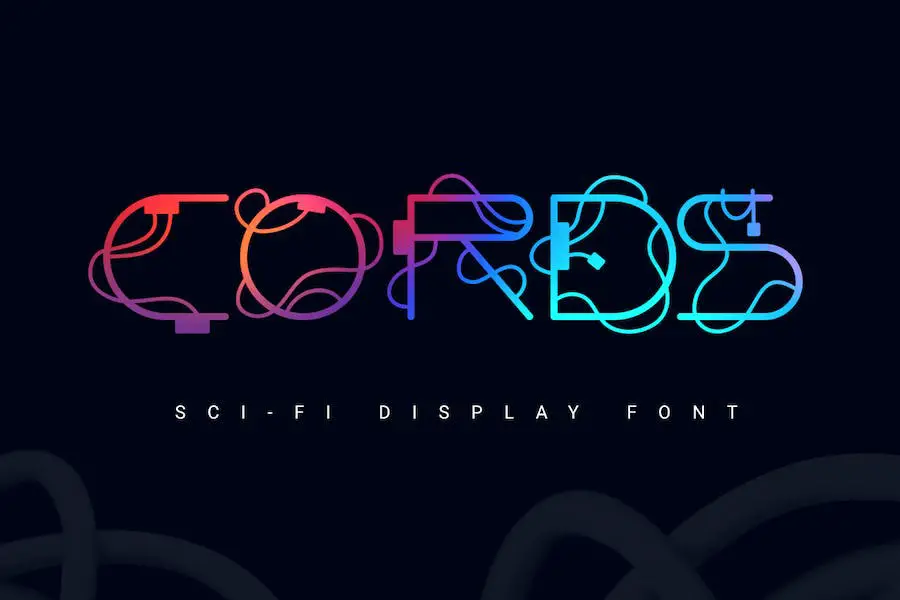
Cords é uma fonte sem serifa exclusiva e elegante que apresenta letras e fios arredondados, dando-lhe uma vibração futurística e de ficção científica. Inspirada no icônico filme Matrix, esta fonte adiciona um toque de emoção e modernidade a qualquer design.
Com letras maiúsculas e capacidade de funcionar bem com fundos claros e escuros, Cords é perfeito para criar títulos curtos atraentes e visualmente atraentes.
A adição de cores às letras realça ainda mais o design geral, tornando-o perfeito para designers gráficos que desejam levar seus projetos para o próximo nível.
Andoria
Andoria é uma fonte moderna projetada para declarações de moda, ficção científica, cinematográficas e exclusivas. Ele tem um charme especial que o torna perfeito para belos títulos, marcas, logotipos e uso em display. Seu design elegante e moderno adiciona um toque de sofisticação a qualquer projeto.
Quer você seja um designer gráfico em busca de aprimorar seus projetos ou um entusiasta da moda que queira fazer uma declaração ousada, Andoria é a escolha perfeita. A versatilidade da fonte permite que ela seja utilizada em diversos contextos, tornando-a obrigatória para designers que buscam elevar seu trabalho.
Esteja você trabalhando em uma capa de revista, um pôster de filme ou um logotipo de roupa, as linhas simples e curvas elegantes de Andoria irão capturar a atenção e deixar uma impressão duradoura.
Com Andoria, seus designs se destacarão da multidão e causarão um impacto memorável. Então, por que esperar? Dê aos seus projetos um toque moderno e elegante com Andoria.
JEDAR
JEDAR é uma fonte techno-sci-fi projetada para quem precisa de uma tipografia de destaque, especialmente para displays, pôsteres e projetos tecnológicos ou astronômicos. Com seus caracteres nítidos e semelhantes a símbolos, esta fonte adicionará um toque de estilo futurista aos seus designs.
Esta fonte de ficção científica é perfeita para dar aos seus projetos um toque futurista e de alta tecnologia. Seus símbolos exclusivos e formatos de caracteres nítidos fazem com que ele se destaque e chame a atenção.
Esteja você projetando um pôster, criando exibições atraentes ou trabalhando em um projeto tecnológico ou astronômico, JEDAR é a fonte que levará seu design para o próximo nível.
As formas nítidas e elegantes dos caracteres do JEDAR lembram símbolos, dando ao seu texto uma aparência distinta e futurística. É perfeito para capturar a essência da tecnologia e as maravilhas do cosmos.
Se você deseja transmitir uma sensação de inovação, explorar o desconhecido ou simplesmente adicionar um toque de ficção científica aos seus designs, esta fonte tem o que você precisa.
Lespace
Lespace é uma fonte de ficção científica moderna do estúdio Drizy, perfeita para seus projetos de ficção científica techno. Com sua variedade de estilos básicos, esta fonte foi projetada especificamente para aprimorar qualquer projeto temático de ficção científica. Criada pelo estúdio Drizy, Lespace oferece tudo que você precisa em uma fonte de ficção científica.
Lespace by Drizy studio é uma fonte moderna e elegante, perfeita para adicionar um toque futurista aos seus projetos. Esteja você projetando um site, criando um logotipo ou trabalhando em uma obra de arte com tema de ficção científica, Lespace tem todos os estilos básicos de que você precisa para dar vida à sua visão.
Esta fonte techno-sci-fi foi projetada com linhas elegantes e bordas nítidas, dando-lhe uma aparência futurista e de alta tecnologia. O design exclusivo da Lespace a diferencia de outras fontes e a torna uma escolha de destaque para qualquer projeto que necessite de uma estética moderna e vanguardista.
Explorar Rover
Rover Explore é uma fonte de ponta que incorpora o futuro e a tecnologia. Ele se enquadra na categoria Futurista e oferece uma mistura perfeita de elementos de techno, ficção científica e estilo espacial.
Se você é um designer gráfico que busca elevar seus projetos com um toque futurista, esta fonte é obrigatória.
Com o Rover Explore, você obtém acesso a uma coleção de 26 fontes de ficção científica de primeira linha. Cada fonte carrega seu próprio estilo único, permitindo que você experimente e encontre a combinação perfeita para seu projeto específico.
Esteja você projetando um site, logotipo, pôster ou qualquer outro empreendimento criativo, essas fontes adicionarão um toque de sofisticação e inovação.
Essas fontes techno-sci-fi são projetadas com precisão e atenção aos detalhes, garantindo que se integrem perfeitamente aos seus designs. A estética elegante e futurista do Rover Explore irá captar a atenção e deixar uma impressão duradoura.
É a escolha perfeita se você deseja criar uma sensação de tecnologia avançada e de outro mundo em seus projetos.
Rochas Espaciais!
Rochas Espaciais! é uma fonte retrô de ficção científica inspirada nas icônicas séries de televisão da década de 1950. Com seu charme vintage e vibrações futuristas, esta fonte é perfeita para designers gráficos que buscam adicionar um toque de nostalgia e estilo da era espacial aos seus projetos.
Os atributos únicos do Space Rocks! faça com que ela se destaque entre outras fontes da categoria. Suas letras ousadas e angulares capturam a essência da ficção científica retrô, transportando instantaneamente os espectadores para uma época de discos voadores e aventuras intergalácticas.
Essa fonte é altamente versátil e pode ser usada para diversos fins de design, desde a criação de logotipo até pôsteres e muito mais.
As linhas limpas e os personagens bem definidos de Space Rocks! garantem legibilidade mesmo em tamanhos maiores, tornando-o ideal para títulos e textos impactantes.
Sua natureza lúdica e atraente o torna uma ótima opção para títulos e cabeçalhos, chamando instantaneamente a atenção e adicionando um toque de personalidade a qualquer design.
Galáxia
Galax é uma nova fonte de ficção científica chamada 'GRVS It' que é perfeita para adicionar um toque futurista ao logotipo de sua equipe ou comunidade. Com seu design elegante e moderno, é a escolha ideal para designers gráficos que buscam aprimorar seus projetos com um tema de ficção científica.
Esta fonte foi criada especificamente para trazer uma sensação de futurismo e criatividade aos seus designs. É perfeito para filmes de ficção científica, videogames ou qualquer projeto que precise de um toque futurista e moderno. É versátil e pode ser usado de várias maneiras para destacar seus designs.
A fonte Galax apresenta letras exclusivas e complexas que certamente chamarão a atenção do seu público. Seu design arrojado e contemporâneo facilita a leitura e acrescenta um toque de profissionalismo a qualquer projeto.
Quer você esteja desenhando um logotipo ou criando um pôster, Galax dará ao seu trabalho uma aparência distinta e moderna.
Uma das grandes vantagens do Galax é a sua adaptabilidade. Ele pode ser redimensionado, dimensionado e manipulado para caber em qualquer projeto sem perder qualidade ou legibilidade.
Isso o torna perfeito para designs impressos e digitais. Ele também suporta diferentes idiomas, para que você possa criar projetos em diferentes idiomas sem complicações.
Bronze de ficção científica
Apresentando Sci Fi Bronze, uma fonte de ficção científica fantástica que pode levar seus projetos de design a um nível totalmente novo. Com seu visual moderno e futurista, esta fonte é perfeita para designers gráficos que desejam adicionar um toque de ficção científica às suas criações.
Uma das características de destaque do Sci-Fi Bronze é seu design elegante e moderno. As linhas limpas e bordas nítidas conferem-lhe um toque futurista, tornando-o a escolha perfeita para qualquer projeto que necessite de um visual moderno e contemporâneo.
Outro grande atributo desta fonte é a sua versatilidade. Esteja você trabalhando em um pôster, logotipo ou design de site, o Sci-Fi Bronze pode se adaptar a qualquer estilo e tema. É uma fonte que pode realmente melhorar a estética geral do seu projeto e destacá-lo da multidão.
Além de sua aparência marcante, Sci-Fi Bronze também oferece uma ampla gama de caracteres e glifos.
Com um extenso conjunto de caracteres, incluindo letras maiúsculas e minúsculas, números e símbolos especiais, você terá todas as ferramentas necessárias para criar designs cativantes e visualmente atraentes.
Surto Sônico
Sonic Surge é uma fonte de exibição ousada e autêntica que celebra formas abstratas em todo o seu brilho eclético. Com seu design elegante e futurista, esta fonte é perfeita para designers gráficos que buscam adicionar um toque de ficção científica aos seus projetos.
As letras fortes e ousadas da fonte marcam presença, capturando a atenção e adicionando uma sensação de energia a qualquer design. Suas formas abstratas e estilo único de letras conferem-lhe uma aparência distinta e moderna que certamente impressionará.
Esteja você trabalhando em um pôster, logotipo ou design de site, o Sonic Surge aprimorará o apelo visual do seu projeto e o destacará da multidão. Sua versatilidade permite que funcione bem tanto em títulos grandes quanto em textos menores, proporcionando flexibilidade em suas escolhas de design.
Uma das características de destaque do Sonic Surge é a atenção aos detalhes. Cada carta é cuidadosamente elaborada, garantindo consistência e legibilidade. As linhas limpas e bordas nítidas da fonte criam uma sensação de precisão, aumentando sua estética futurista.
Andro Futurista
Andro Futuristic é uma fonte hipnotizante sem serifa que exala uma vibração futurística. Esta fonte foi meticulosamente elaborada com atenção precisa aos detalhes, resultando em curvas perfeitas e um design impecável.
Com a sua versatilidade, o Andro Futuristic pode complementar perfeitamente uma vasta gama de projetos, permitindo-lhe libertar a sua criatividade sem restrições.
Esteja você projetando um pôster de filme de ficção científica, um site futurista ou um logotipo inovador, Andro Futuristic é a fonte ideal. Sua aparência elegante e polida irá cativar o seu público, mergulhando-o instantaneamente em um mundo futurista.
A fonte Andro Futuristic possui uma ampla gama de atributos que a tornam obrigatória para designers gráficos. Oferece uma estética clean e minimalista, perfeita para conseguir um visual moderno e vanguardista.
As curvas contínuas e as linhas suaves da fonte garantem legibilidade e harmonia visual, melhorando o apelo geral de seus designs.
Arcádia
Arcadia – uma fonte de exibição Sans Serif para jogos esportivos elegante e moderna que é perfeita para todos os seus próximos projetos de design. Quer você seja um designer gráfico em busca de aprimorar seus projetos ou simplesmente alguém que aprecia uma boa tipografia, a Arcadia está aqui para fazer uma declaração.
Com sua vibração esportiva e futurista, Arcadia adiciona um toque de emoção e energia a qualquer design. As linhas simples e as formas arrojadas desta fonte a tornam ideal para títulos, logotipos e materiais de branding.
Ele realmente captura a essência do gênero de ficção científica, tornando-o obrigatório para designers que trabalham em projetos futuristas ou relacionados à tecnologia.
Arcadia possui uma gama de atributos atraentes que a diferenciam de outras fontes. Em primeiro lugar, o seu design sem serifa confere-lhe um aspecto contemporâneo e minimalista, tornando-o incrivelmente versátil.
Esteja você trabalhando em um pôster, site ou até mesmo em uma interface de jogo, o Arcadia garantirá que seu texto se destaque e chame a atenção.
MORTON
MORTON é uma fonte que captura a essência do vasto e curioso mundo do espaço. Com seu design exclusivo, permite explorar este reino fascinante em seus projetos de design gráfico.
As letras maiúsculas apresentam um recorte no canto, adicionando um toque diferenciado, enquanto as letras minúsculas permanecem totalmente fixadas para um visual coeso.
O design da MORTON é perfeito para adicionar um clima de ficção científica aos seus projetos. Seus cantos recortados dão uma sensação ousada e futurista, enquanto as letras minúsculas totalmente anexadas mantêm uma sensação de coesão. Esta fonte é ideal para transmitir a maravilha e o mistério do espaço em seus designs.
Uma das características de destaque da MORTON é a sua versatilidade. Esteja você trabalhando em um pôster, site ou logotipo, essa fonte pode se adaptar perfeitamente a vários projetos de design. Suas linhas simples e estilo exclusivo o tornam uma excelente escolha para qualquer design de ficção científica ou com tema espacial.
Galáxia
Galaxy é uma fonte modular, geométrica e levemente condensada que visa aprimorar a exibição de seus projetos. Como designer gráfico em busca de fontes para elevar seus designs, o Galaxy apresenta uma excelente opção.
Com características únicas, essa fonte se destaca e acrescenta um toque de sofisticação ao seu trabalho.
O design modular do Galaxy permite fácil organização e personalização, tornando-o versátil para uma ampla gama de projetos. Sua natureza geométrica confere uma aparência clean e moderna, enquanto o estilo condensado ajuda a garantir que seu texto permaneça compacto e visualmente atraente.
Esteja você trabalhando em pôsteres, logotipos ou materiais de marca, o Galaxy pode trazer uma sensação de elegância e profissionalismo. Seu design focado na exibição o torna perfeito para chamar a atenção do espectador e criar um impacto visual memorável.
Atecha Sport
'Atecha Sport é uma fonte que se inspira nos mundos emocionantes dos jogos, tecnologia e esportes. Captura a essência do progresso e da inovação nestas áreas, tornando-o uma escolha perfeita para designers gráficos que procuram aprimorar os seus projetos com um toque de estilo futurista.
Com o seu design elegante e moderno, o Atecha Sport exala uma sensação de energia e dinamismo. Ele adiciona um elemento único e atraente a qualquer design, seja um logotipo de jogo, um pôster esportivo ou um site com tema tecnológico.
A estética ousada e futurista das fontes faz com que elas se destaquem da multidão, deixando uma impressão duradoura nos espectadores.
A versatilidade do Atecha Sport é outro aspecto que o diferencia. Adapta-se perfeitamente a vários contextos de design, seja digital ou impresso. Suas linhas limpas e nítidas tornam-no facilmente legível em diferentes tamanhos, garantindo que sua mensagem chegue claramente ao seu público.
Esteja você trabalhando em um site, no layout de uma revista ou em um gráfico de mídia social, Atecha Sport é uma escolha confiável que oferece resultados.
Leegione
Leegione é uma fonte futurista de ficção científica neon que adiciona um toque único e cativante aos seus projetos. Com seu estilo futurista, esta fonte é perfeita para criar logotipos atraentes que deixarão uma impressão duradoura.
Esteja você projetando um pôster de filme de ficção científica ou um site de alta tecnologia, Leegione certamente levará seu projeto para o próximo nível.
O design elegante e moderno da Leegione faz com que ela se destaque de outras fontes. Seu brilho neon e bordas nítidas dão uma sensação futurística, transportando instantaneamente os espectadores para um mundo de ficção científica.
Essa fonte é versátil e funciona bem em aplicações ousadas e sutis, tornando-a uma ótima opção para uma ampla variedade de projetos.
Uma das grandes vantagens de Leegione é a sua legibilidade. Apesar de seu design futurista, a fonte permanece legível e não sacrifica a clareza pelo estilo. Isto garante que a sua mensagem será sempre transmitida com clareza, mesmo nos designs mais visualmente marcantes.
Quadros Espaciais
Space Boards é uma fonte sans-based que oferece uma combinação única de caracteres minúsculos e maiúsculos, dando aos seus designs uma aparência futurista e moderna.
Esta fonte é perfeita para designers gráficos que buscam aprimorar o design geral de seus projetos, incorporando um toque de estética de ficção científica.
Com sua aparência elegante e moderna, Space Boards certamente chamará a atenção dos espectadores e adicionará um toque contemporâneo a qualquer design.
Esteja você trabalhando em um logotipo, pôster ou site, esta fonte é uma ótima opção para criar um design visualmente impressionante e inovador.
Satélite
Sattelar é uma fonte futurística inspirada em ficção científica, filmes e livros. Ele adiciona um toque futurista aos seus projetos de design, capturando a essência do gênero de ficção científica.
Com seu design elegante e moderno, Sattelar é perfeito para criar manchetes, títulos e logotipos atraentes que transportam instantaneamente seu público para um mundo futurista.
Os atributos da Sattelar são o que a diferenciam das demais fontes. Suas linhas simples e formas geométricas conferem-lhe um visual elegante e moderno, tornando-o ideal para designs contemporâneos.
Esteja você trabalhando em um pôster para uma convenção de ficção científica ou projetando um site para uma empresa de tecnologia, o estilo futurista da Sattelar dará aos seus projetos uma sensação única e inovadora. Sua versatilidade permite que seja utilizado em diversas aplicações de design, seja em mídia impressa ou digital.
Melhores fontes de ficção científica gratuitas
Quer levar seus projetos de design gráfico para o próximo nível? Não procure mais, nossa seleção das melhores fontes de ficção científica gratuitas! Reserve um momento para navegar por essas fontes interessantes e eleve seus designs com um toque de estilo futurista.
Neo-Ficção Científica
Neo Sci-Fi é uma fonte de última geração que levará seus projetos de design gráfico a um nível totalmente novo. Criada por Bryan Augusto, esta fonte foi projetada especificamente para quem deseja adicionar um toque futurista e de ficção científica aos seus designs.
Um dos atributos de destaque do Neo Sci-Fi é seu visual elegante e moderno. Com formas nítidas e geométricas, esta fonte captura perfeitamente a essência da estética da ficção científica. Suas linhas limpas e detalhes futuristas fazem dele a escolha ideal para projetos que exigem um toque futurista e de alta tecnologia.
Além disso, Neo Sci-Fi oferece uma ampla variedade de gramaturas e estilos, permitindo que você experimente e encontre a combinação perfeita para seus designs. Esteja você adicionando títulos, legendas ou corpo de texto, esta fonte tem o que você precisa.
Sua versatilidade garante que você possa usá-lo em vários projetos de design, de sites a pôsteres e muito mais.
Outra grande característica do Neo Sci-Fi é a sua legibilidade. Apesar de seu design elegante e exclusivo, a fonte permanece altamente legível, garantindo que seu público possa compreender facilmente o conteúdo. Esse equilíbrio entre estilo e funcionalidade é o que diferencia a Neo Sci-Fi de outras fontes de ficção científica.
Caixa de ficção científica
Sci-Fi Box da Fontalics Studio é uma fonte perfeita para designers gráficos que buscam aprimorar seus projetos com um toque futurista e de ficção científica. Com seus designs elegantes e inovadores, o Sci-Fi Box certamente levará seus designs para o próximo nível.
Um dos atributos de destaque do Sci-Fi Box é sua versatilidade. Cada fonte da coleção tem seu próprio estilo distinto, variando de ousado a elegante e moderno.
Isso permite que os designers encontrem o ajuste perfeito para seu projeto específico, seja um pôster de filme, capa de videogame ou site futurista.
Outra grande característica do Sci-Fi Box é a atenção aos detalhes. Cada fonte é meticulosamente elaborada, com linhas precisas e designs complexos que capturam a essência da ficção científica.
Esteja você buscando uma vibração retrô dos anos 80 ou um visual elegante e minimalista, o Sci-Fi Box tem uma fonte que atenderá às suas necessidades.
Queda de energia
Blackout by Alpaprana é uma fonte poderosa, perfeita para designers gráficos que buscam aprimorar o design de seus projetos.
Esta fonte de ficção científica adiciona um toque futurista e ousado a qualquer design, fazendo com que ele se destaque da multidão. Com seu estilo elegante e ousado, Blackout certamente cativará e envolverá os espectadores.
Os atributos do Blackout são o que o tornam verdadeiramente excepcional. Suas letras únicas e intrincadas proporcionam um toque moderno e de alta tecnologia, perfeito para temas de ficção científica.
Os ângulos agudos e as formas geométricas criam uma sensação de ousadia e inovação. A atenção aos detalhes em cada letra torna o Blackout uma escolha visualmente deslumbrante.
Mas o que realmente diferencia o Blackout é a sua versatilidade. Ele pode ser usado em uma variedade de projetos de design, desde branding e logotipos até pôsteres e folhetos.
Sua aparência arrojada e imponente o torna ideal para manchetes ou títulos, enquanto sua legibilidade garante que também possa ser usado para corpo de texto. O blackout adiciona sem esforço uma aparência profissional e sofisticada a qualquer design.
Futuro de afinidade
Affinity Future, criada pela Checkered Ink, é uma fonte fantástica que levará seus projetos de design de ficção científica para o próximo nível. Com seu design futurista e elegante, esta fonte é perfeita para adicionar um toque de ficção científica ao seu trabalho de design gráfico.
O Affinity Future irá chamar instantaneamente a atenção do seu público e dar aos seus projetos um visual único e moderno.
Um dos atributos de destaque do Affinity Future é a sua versatilidade. Ele pode ser usado para uma variedade de projetos de design, desde cabeçalhos e logotipos de sites até pôsteres e capas de álbuns.
Essa fonte é altamente legível, facilitando a leitura de sua mensagem pelo público, ao mesmo tempo que mantém a estética de ficção científica.
Outra grande característica desta fonte é seu extenso conjunto de caracteres. O Affinity Future inclui uma ampla variedade de caracteres e ligaduras alternativos, permitindo que você personalize seu texto e torne-o realmente seu.
Você pode criar facilmente uma tipografia atraente e visualmente interessante experimentando diferentes combinações de caracteres.
Grande Espaço
Grand Space by typefactory é uma fonte de ficção científica perfeita para designers gráficos que buscam aprimorar seus projetos com um toque futurista. Esta fonte traz uma sensação de espaço e tecnologia aos seus designs, tornando-a ideal para projetos com tema de ficção científica ou qualquer coisa que precise de uma estética elegante e moderna.
Com suas letras ousadas e distintas, Grand Space captura a essência do gênero de ficção científica e adiciona um toque único à sua tipografia.
Um dos principais atributos do Grand Space é a sua versatilidade. Ele pode ser usado em uma ampla variedade de projetos de design, desde pôsteres e capas de livros até sites e logotipos. As linhas limpas e as bordas nítidas da fonte conferem-lhe uma aparência futurista, ao mesmo tempo que é fácil de ler.
Esteja você projetando um pôster de filme ou criando um site com tema de ficção científica, o Grand Space fará com que seu texto se destaque e cative seu público.
Espigão Fala
Spike Speak, criada pela Checkered Ink, é uma fonte fantástica que todo designer gráfico precisa em sua coleção. Esta fonte inspirada na ficção científica é perfeita para adicionar um toque futurista a qualquer projeto. Com seu design elegante e ousado, o Spike Speak levará seus designs para o próximo nível.
Os atributos do Spike Speak são o que realmente o diferenciam. Suas letras em negrito e angulares fazem uma declaração forte e chamam a atenção imediatamente. As linhas simples e as bordas nítidas conferem-lhe uma aparência moderna e de alta tecnologia, tornando-o ideal para temas de ficção científica e futuristas.
Esteja você trabalhando em um logotipo, pôster ou site, o Spike Speak adicionará um elemento distinto e cativante ao seu design.
Mas o Spike Speak não é apenas visualmente impressionante, é também incrivelmente versátil. Ele vem em vários pesos e estilos, permitindo que você experimente e encontre o ajuste perfeito para o seu projeto.
Se você deseja um título ousado e impactante ou um subtexto mais sutil e elegante, o Spike Speak tem o que você precisa. Além disso, suporta vários idiomas, garantindo que possa ser usado por designers de todo o mundo.
Colônia
Colony by CS Design é uma fonte fantástica, perfeita para designers gráficos que buscam aprimorar o design de seus projetos de ficção científica. Esta fonte traz uma sensação futurista e espacial a qualquer design, tornando-a ideal para criar visuais cativantes.
Colony possui uma estética elegante e moderna, com linhas simples e formatos de letras exclusivos que certamente chamarão a atenção. Seu visual arrojado e futurista adiciona um toque de entusiasmo e criatividade a qualquer projeto, tornando-o uma escolha popular entre os designers.
Uma das características marcantes do Colony é sua versatilidade. Ele pode ser usado para uma ampla variedade de projetos de design, incluindo logotipos, marcas, pôsteres e muito mais. Oferece uma variedade de pesos e estilos, permitindo que os designers personalizem suas criações para atender às suas necessidades específicas.
Estroboscópio
Strobo, criada pela Grudnuk Creations, é uma fonte perfeita para designers gráficos que buscam aprimorar o design de seus projetos. Ele oferece uma sensação única e futurista, ideal para designs com temas de ficção científica.
Com Strobo, você pode transformar instantaneamente seus designs em algo de outro mundo. Suas linhas elegantes e nítidas lembram a tecnologia futurista, conferindo aos seus projetos um visual moderno e vanguardista.
Esta fonte de ficção científica vem com uma variedade de atributos que certamente impressionarão qualquer designer gráfico. Seu design limpo e geométrico garante legibilidade mesmo em tamanhos pequenos, tornando-o versátil para diversas aplicações de design.
O Strobo não só se destaca em termos de estética, mas também oferece praticidade. A fonte inclui uma ampla variedade de caracteres, símbolos e sinais de pontuação, permitindo incorporá-la perfeitamente em seus designs, sem limitações.
perguntas frequentes
Fontes de ficção científica são fontes frequentemente usadas em designs, filmes, livros e outras mídias com temas de ficção científica para criar uma atmosfera futurística ou de outro mundo.
Essas fontes geralmente apresentam formatos de letras exclusivos e futuristas, muitas vezes incorporando elementos como bordas nítidas, formas geométricas ou símbolos de alta tecnologia.
As fontes de ficção científica ganharam popularidade devido à sua capacidade de evocar instantaneamente uma sensação de elementos futuristas ou fantásticos. Eles ajudam a criar uma experiência visualmente impressionante e envolvente para leitores, espectadores ou usuários, aprimorando a estética geral e o tema dos projetos de ficção científica.
Quer seja o título de um filme, a capa de um livro ou o design de um site, as fontes de ficção científica adicionam uma dose extra de emoção e cativam a atenção do público.
Os termos de licenciamento de cada fonte podem variar, por isso é importante verificar a licença específica para uso comercial. Algumas fontes de ficção científica podem ser gratuitas para uso pessoal e comercial, enquanto outras podem exigir licença ou pagamento para fins comerciais.
Sempre certifique-se de ler as informações de licença fornecidas com a fonte para garantir a conformidade.
Conclusão
Para encerrar, abordamos muito neste artigo sobre as 26 melhores fontes de ficção científica.
Desde a importância de escolher a fonte certa para seus projetos até o impacto que ela pode ter no design geral, esperamos que você tenha adquirido uma compreensão valiosa de como as fontes podem aprimorar suas criações de ficção científica.